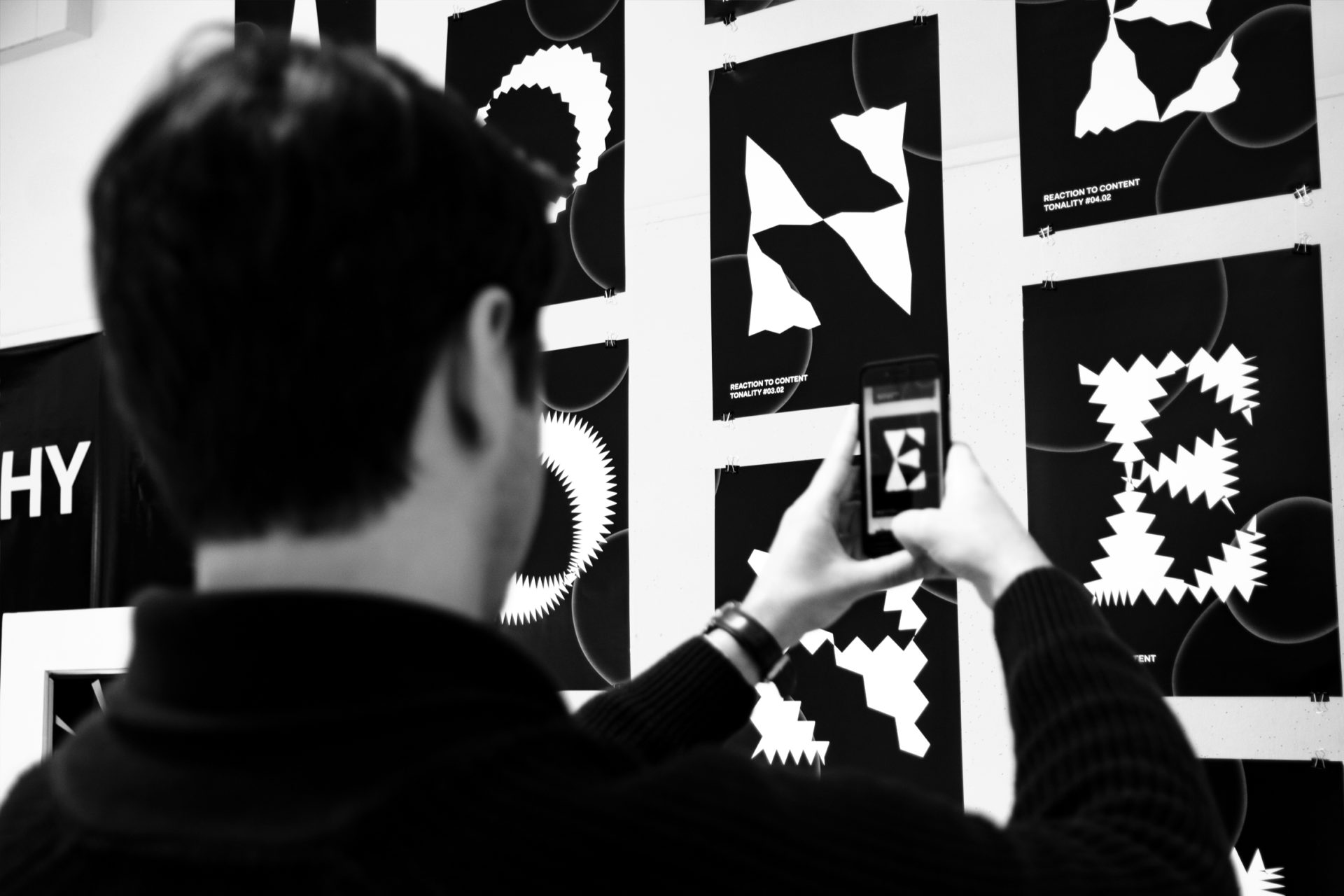
Relevancia
Variable Fonts – Reactive Typography es un proyecto de investigación que explora el potencial de las fuentes variables. La propuesta se materializa como una exhibición interactiva que mezcla medios analógicos y digitales, integrando una publicación impresa, carteles reactivos y el uso de realidad aumentada para fusionar el formato estático con el dinámico.
Su aportación reside en demostrar que la morfología de los glifos puede interactuar con estímulos del entorno. El sistema emplea tecnologías web (HTML, CSS y JavaScript) para vincular datos externos con los ejes de la fuente variable, lo cual automatiza las variaciones de los tipos en respuesta a la interacción del espectador.
La relevancia de este proyecto para la investigación es que emplea tecnologías web para explotar el potencial de la tipografía variable.